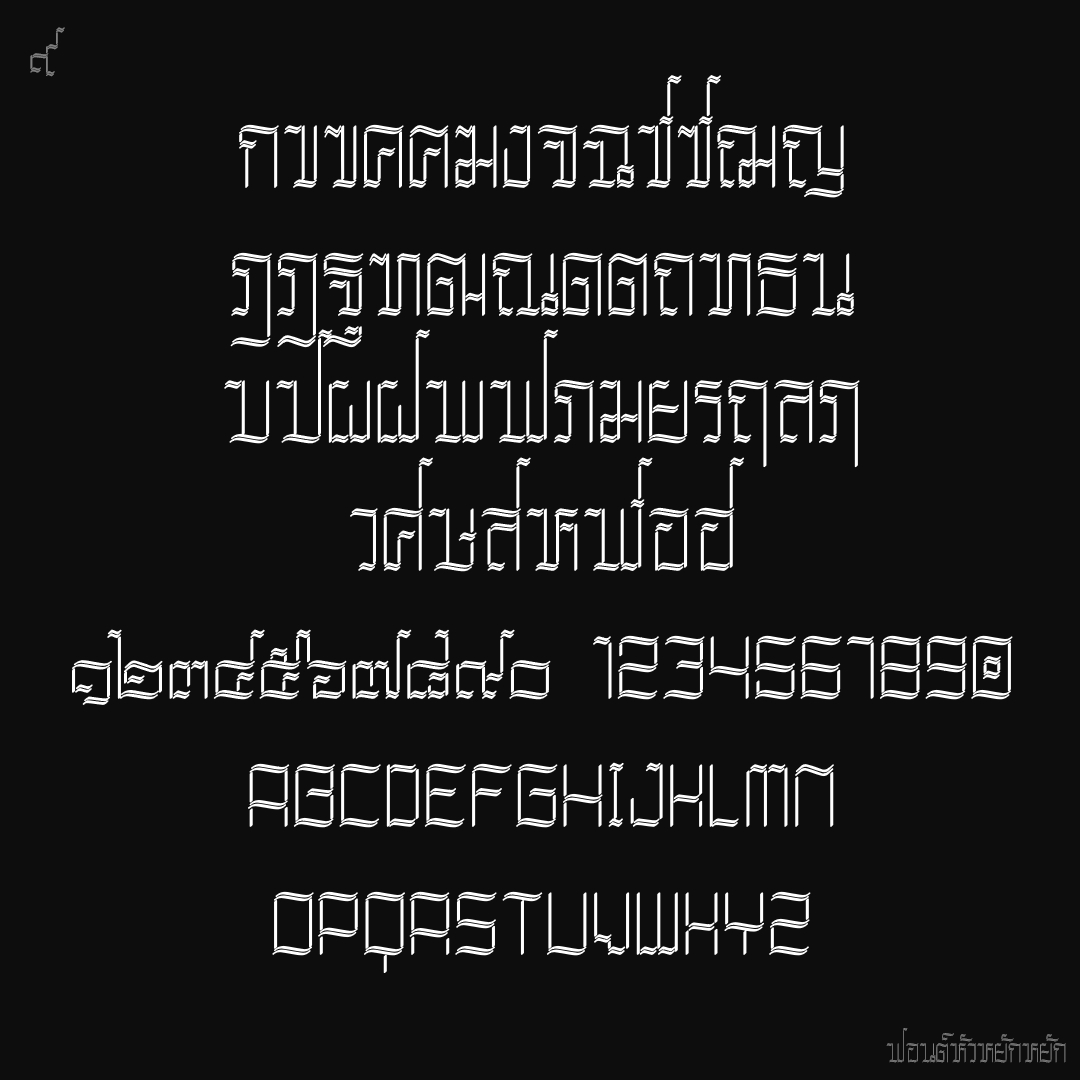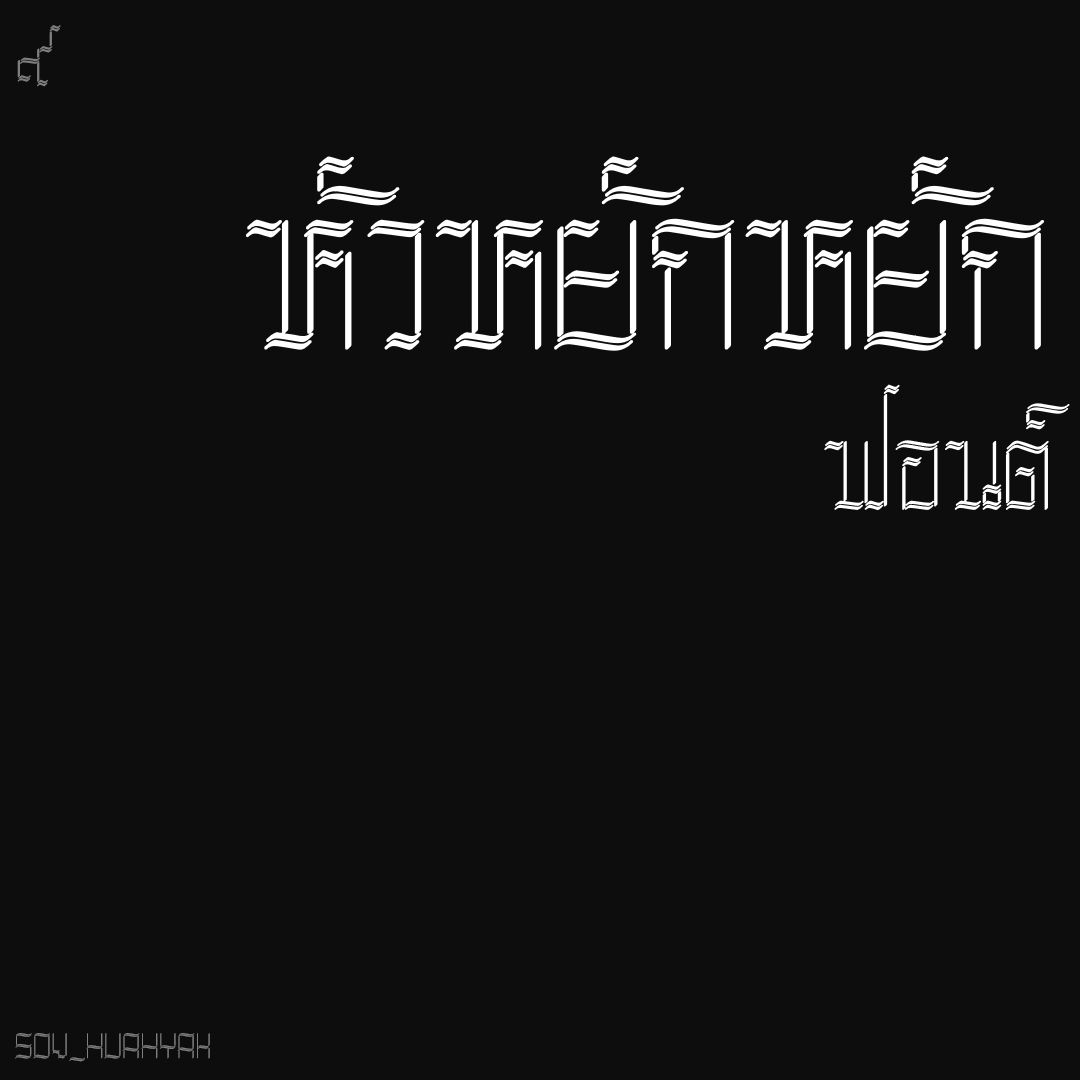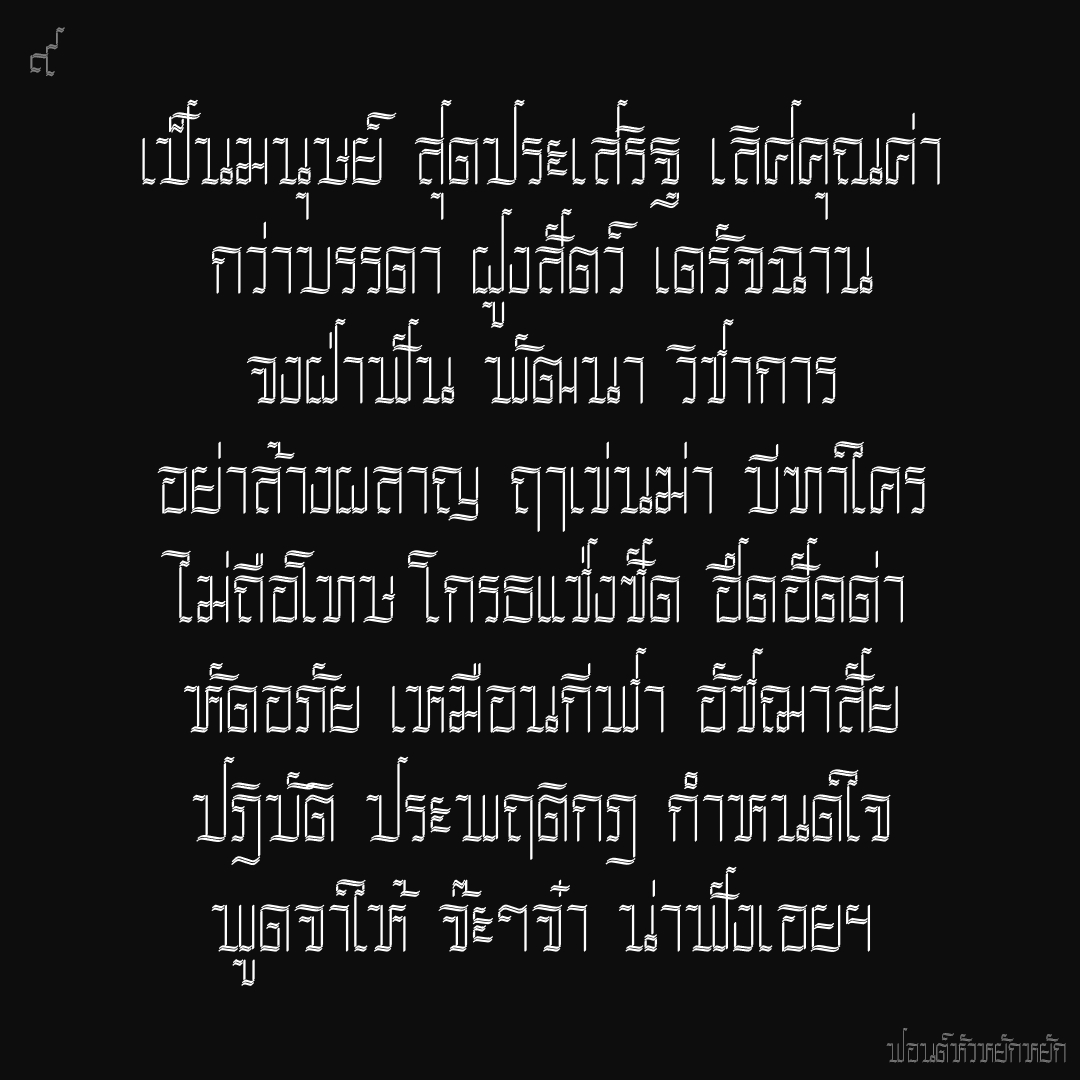
ฟอนต์ หัวหยักหยัก
ฟอนต์หยักๆ เงาลางๆจากลายมืออักษรประดิษฐ์ที่มักใช้เขียนปกรายงานสมัยเด็ก เนื่องจากลายมือปกติไม่สวย เอาปกสวยไว้ก่อน (สวยได้แค่นี้แหละ) พอคุณครูเปิดเข้าไปอ่านรายงาน แทบปาสมุดทิ้ง เพราะกระดาษฟุลสแก๊ปเต็มไปด้วยไก่เขี่ย (ไม่ตรงปก..มีมาแต่สมัยนู้นนนน)
ชื่อฟอนต์ : หัวหยักหยัก
ฟอนต์หยักๆ เงาลางๆจากลายมืออักษรประดิษฐ์ที่มักใช้เขียนปกรายงานสมัยเด็ก เนื่องจากลายมือปกติไม่สวย เอาปกสวยไว้ก่อน (สวยได้แค่นี้แหละ) พอคุณครูเปิดเข้าไปอ่านรายงาน แทบปาสมุดทิ้ง เพราะกระดาษฟุลสแก๊ปเต็มไปด้วยไก่เขี่ย (ไม่ตรงปก..มีมาแต่สมัยนู้นนนน)